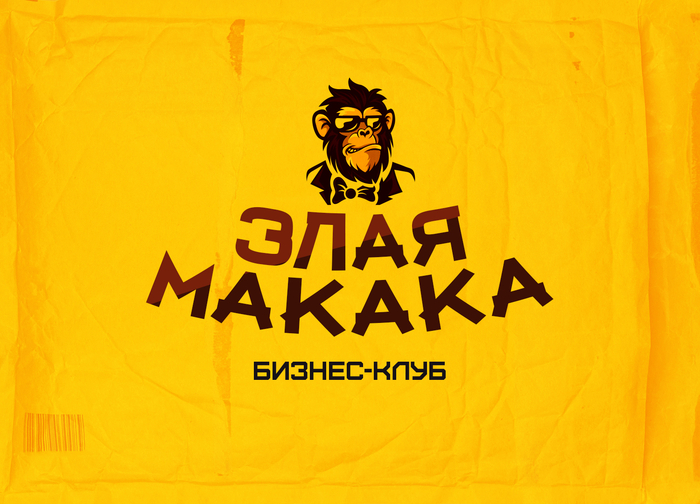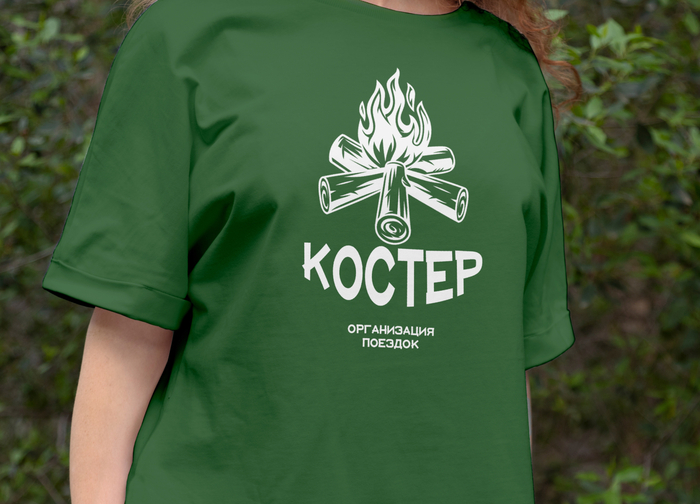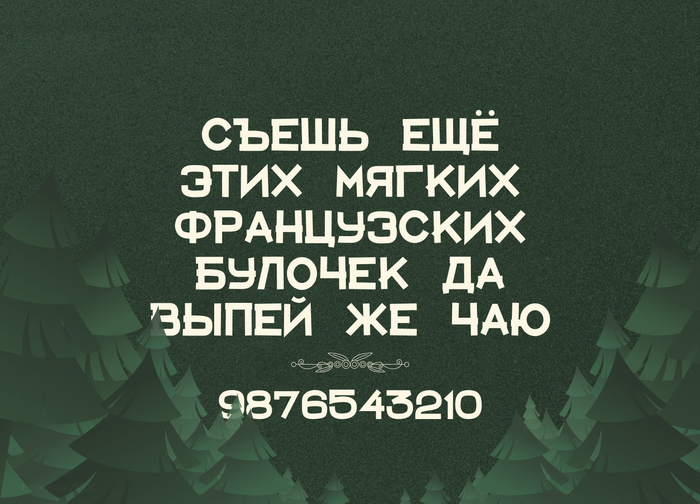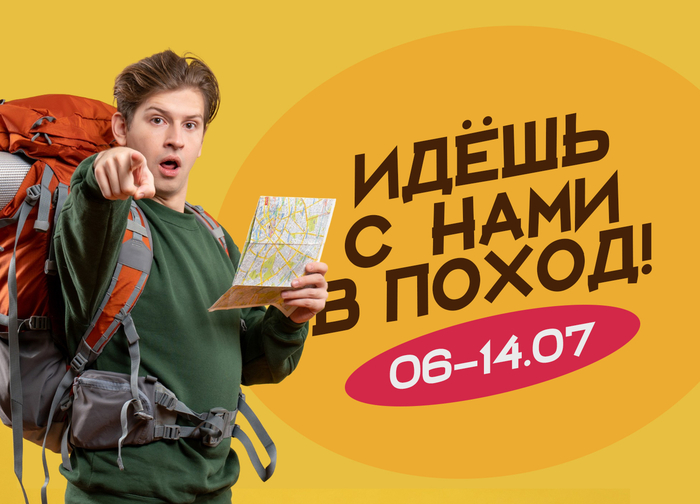
Шрифт Homevideo. Пиксели
Homevideo. Пиксельный шрифт со странным названием) Что-то со временем старых операционок или приставки денди.
В общем играйся) Только не долго! Кинескоп посадишь!
Шрифт Nunito. Или «Нунитооооо!» Фраза которую не хочется услышать от заказчика 😂 А если серьезнее. То ловите хорошо читаемый, вариативный гротеск. Есть 2 варианта: с мягкими краями и более острыми. (Добавил оба) В отличие от того же монтсеррата он более компактный по ширине.
Шрифт Debby. Рисованный шрифт для детских тематик.
Вы можете использовать его для чего угодно: от приглашения на свадьбу, плаката с цитатой, логотипа, поздравительных открыток и т. д.
Murs Memes. Доделал еще одну презентацию. Пухлый шрифт с необычными буквами в комплекте.
Странно, что я не опубликовал его раньше) Вполне читаемый шрифт, но не лишенный изюминки.
Привет) Ловите новую презентацию. Шрифт Mirra. Декоративный шрифт с кириллицей.